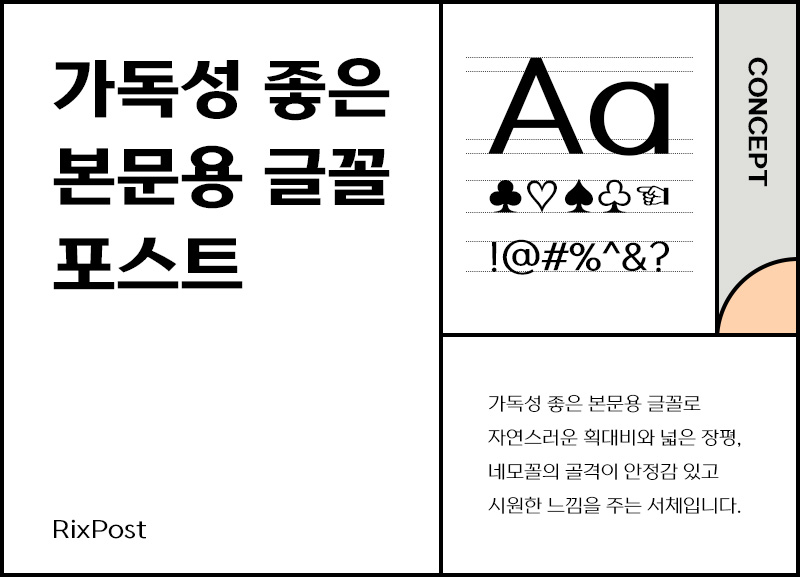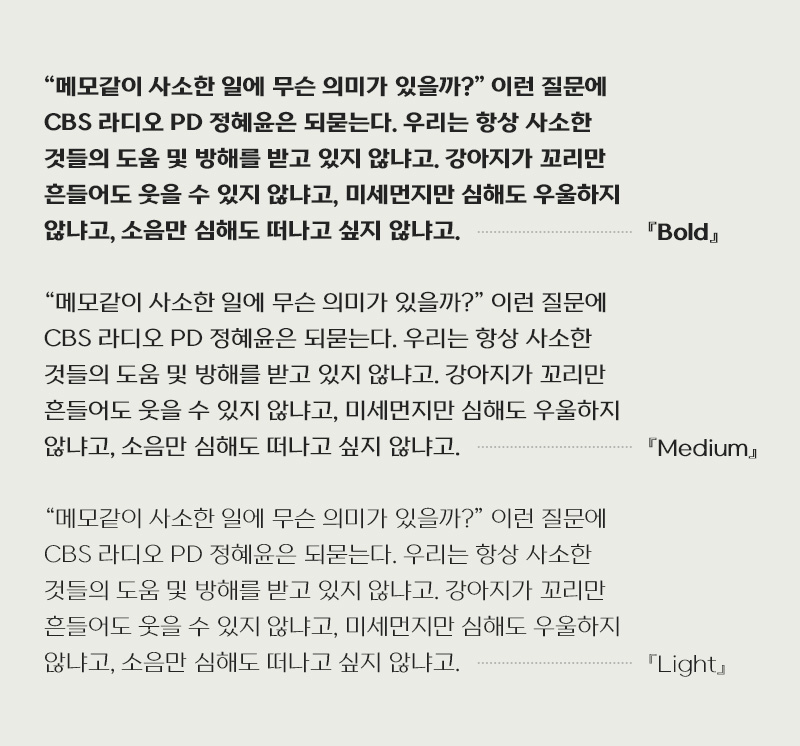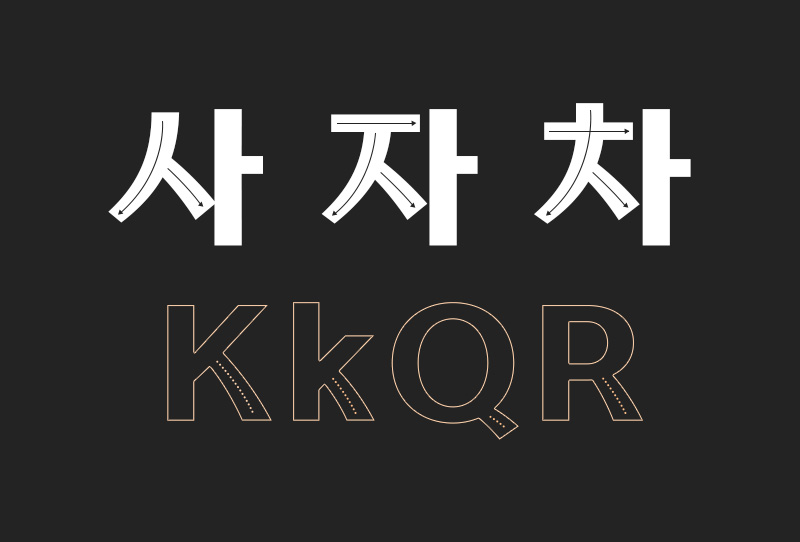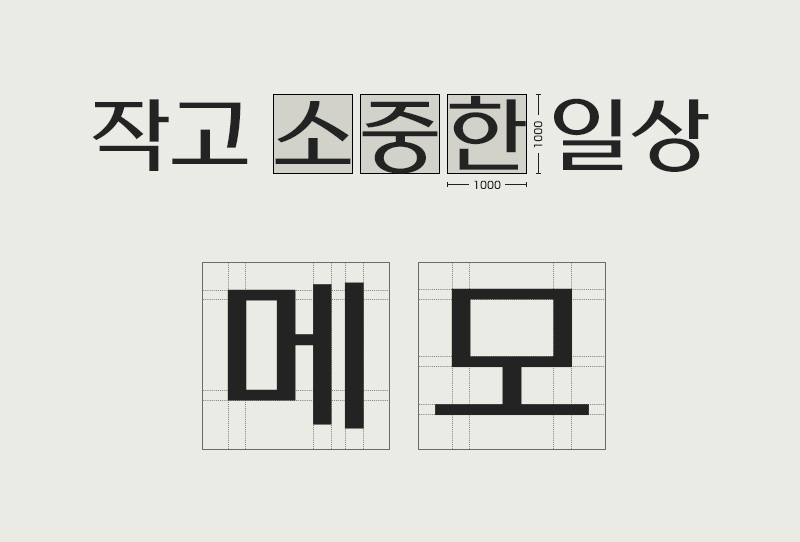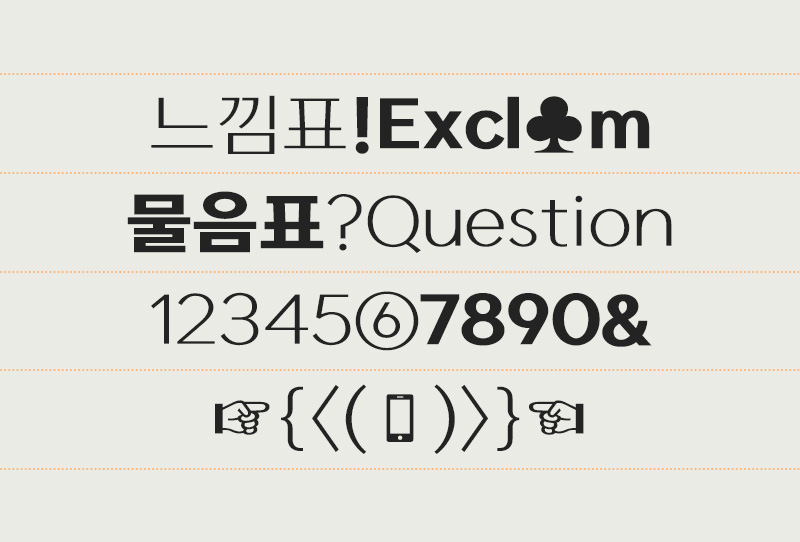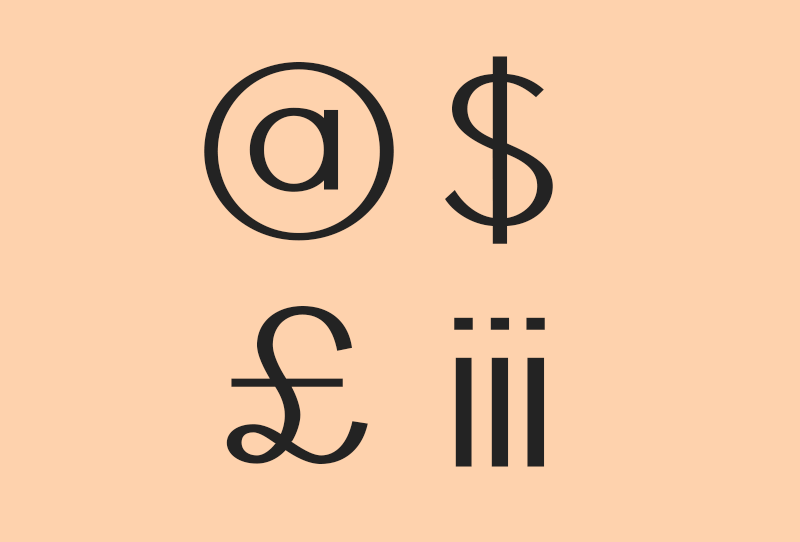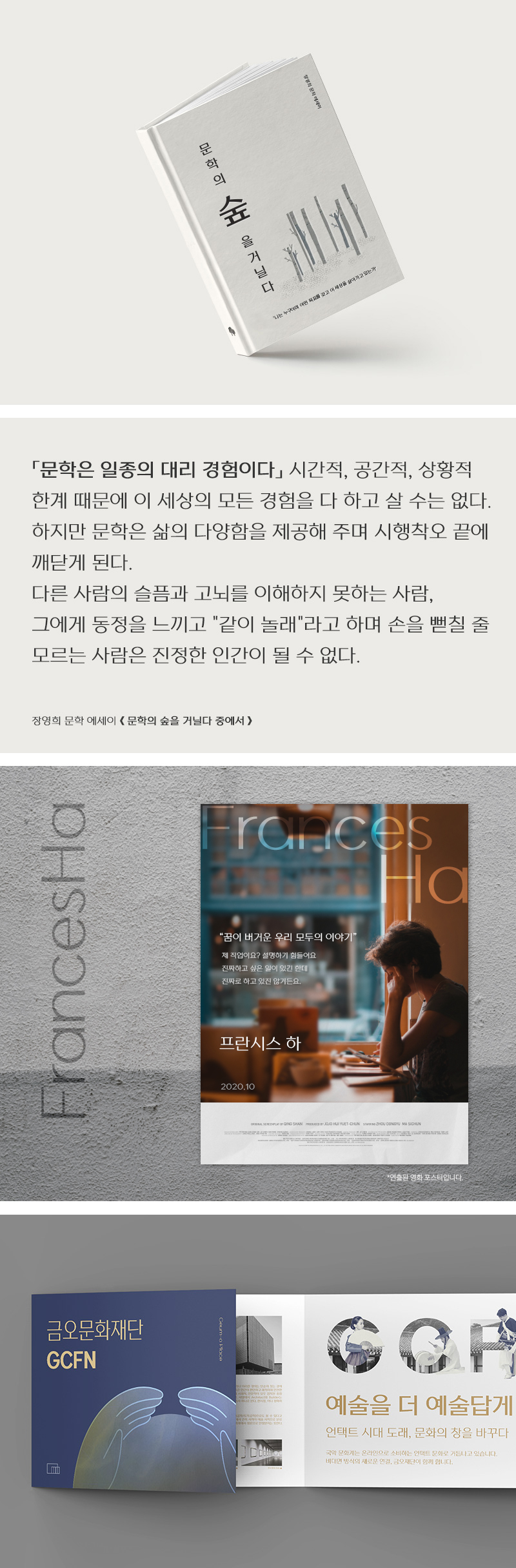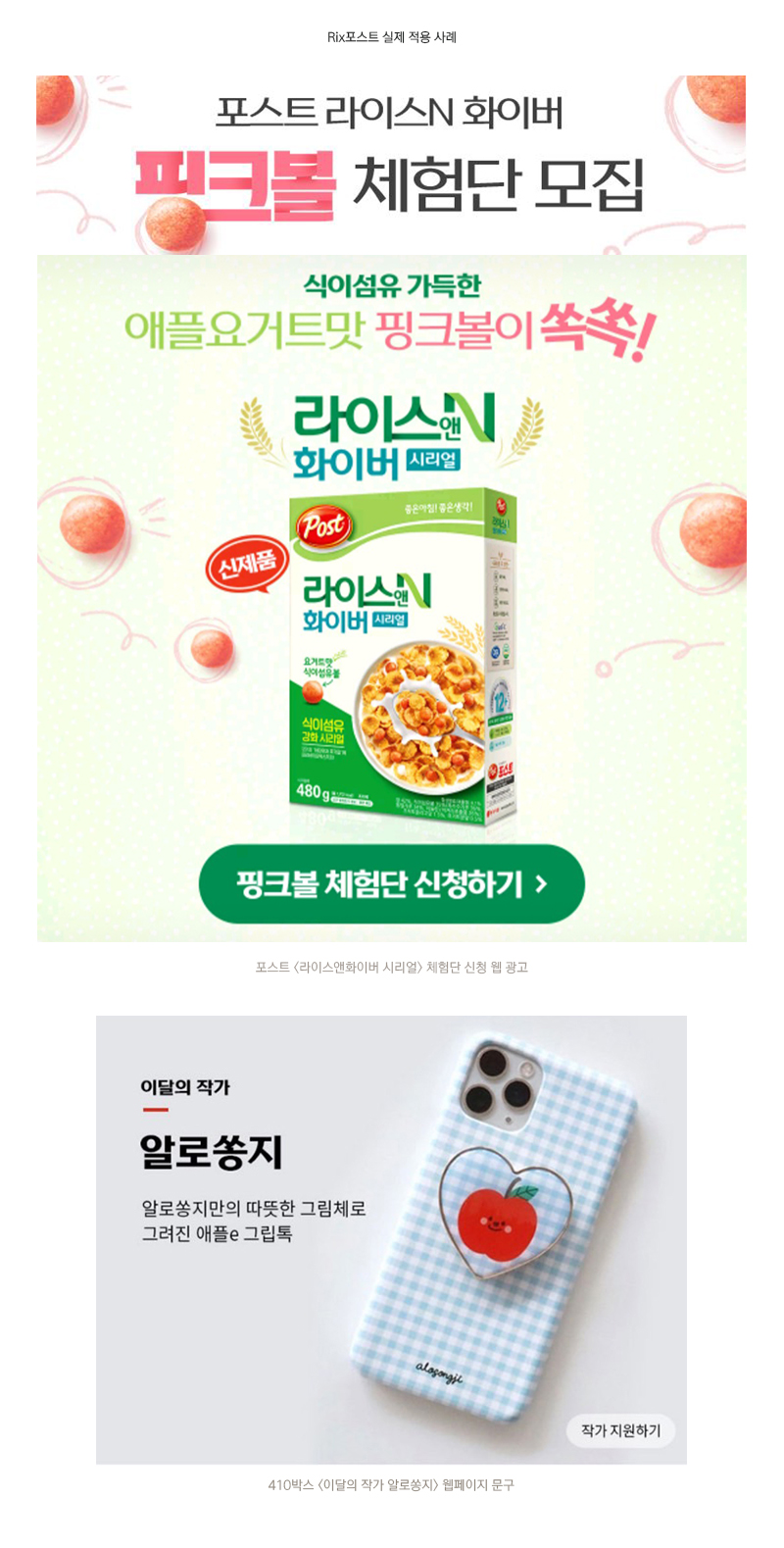
Rix포스트
3 종 - Bold, Medium, LightRix포스트는 자연스러운 획대비와 높은 가독성을 가진 본문용 글꼴입니다.
넓은 장평의 골격이 안정감을 주며, 시원하고 산뜻한 느낌을 주는 서체입니다.
| 폰트명 | Rix포스트 / RixPost |
| 폰트디자인 | 김근영 |
| 디자인디렉팅 | 박용락 |
| 폰트구성 | 한글 2,350자 + 추가자 430자 / 라틴 94자 / 약물 986자 |
| 출시년도 | 2020년 |